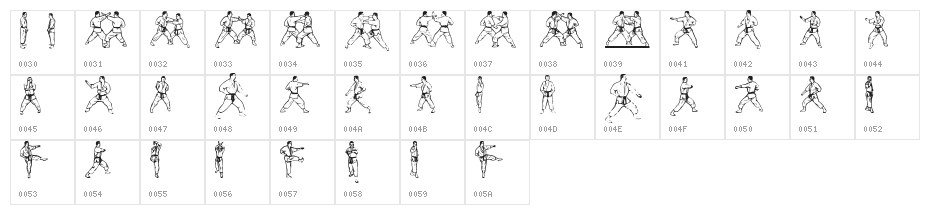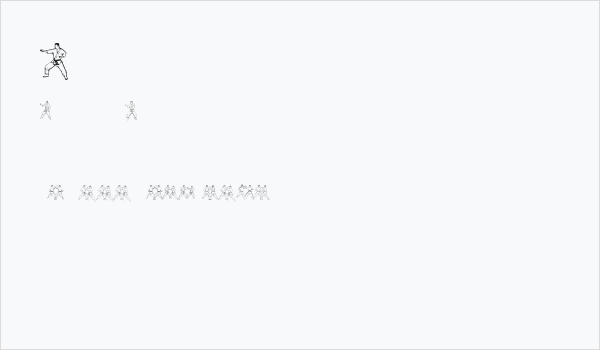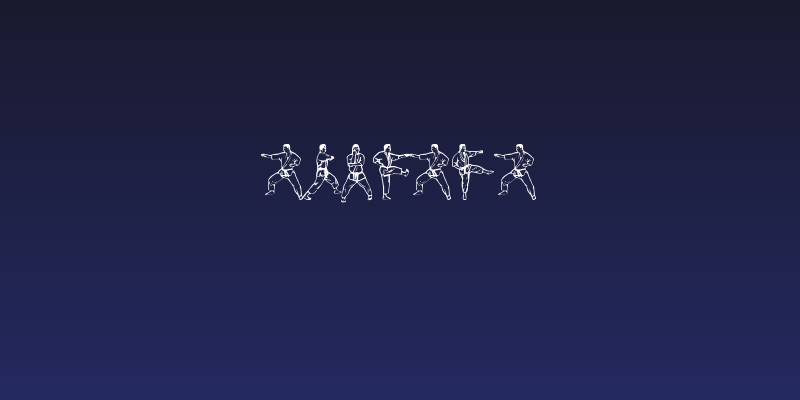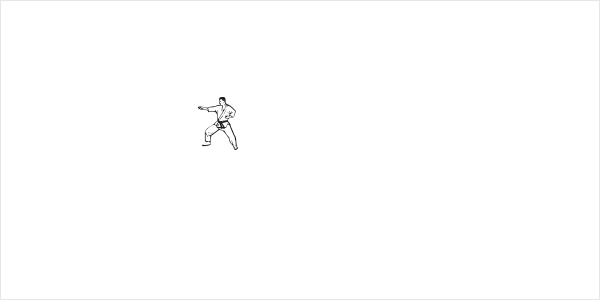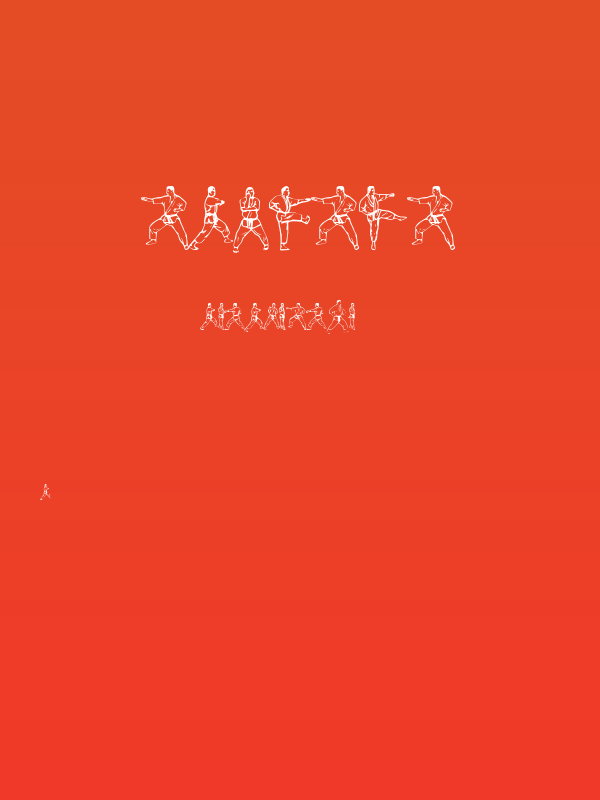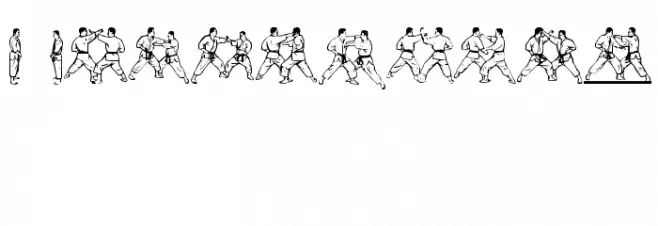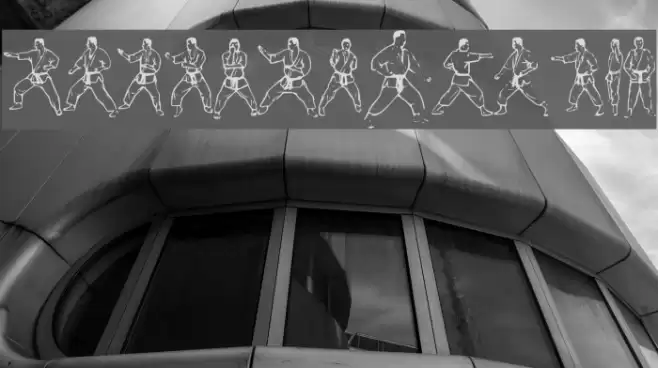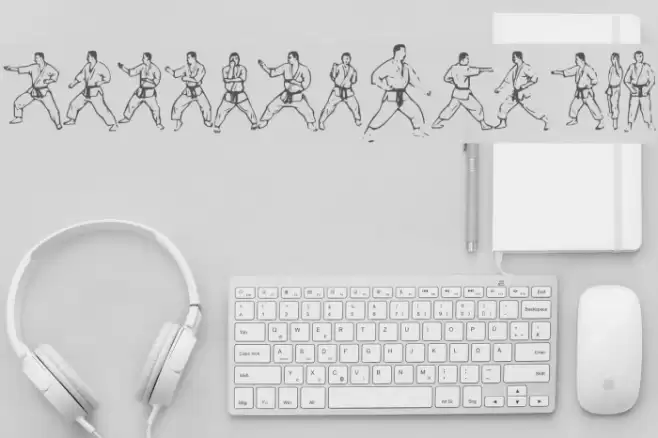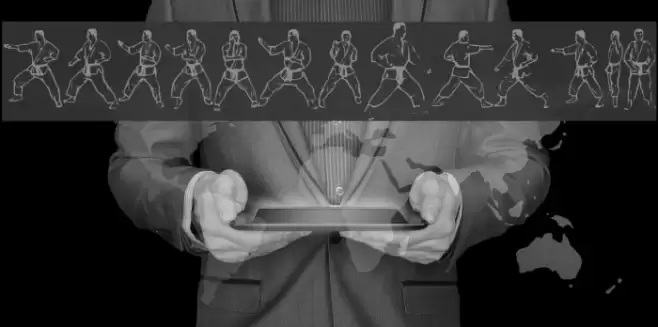
Atewaza Font
✎ Dingbats
| Категория | Dingbats |
| Ширина | Expanded |
| Общий стиль | Thematic, illustrative, action-oriented |
| Область применения | Headlines, logos, thematic branding |
| Рекомендуемые проекты | Martial arts event posters, dojo branding, sports apparel design, themed invitations, and action-oriented graphic projects. |